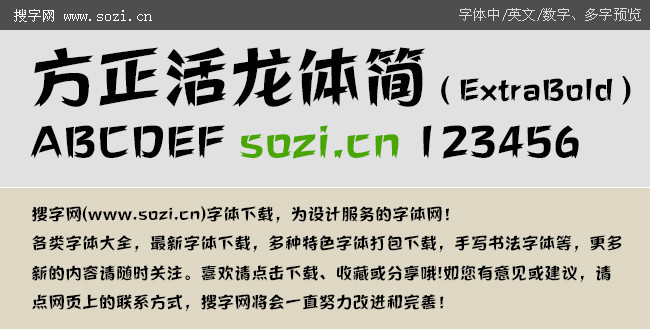
方正活龍?bào)w簡(jiǎn)ExtraBold
搜字網(wǎng)提供一款方正活龍?bào)w簡(jiǎn)中文字體下載,方正活龍?bào)w簡(jiǎn)是方正字庫(kù)全新開(kāi)發(fā)的一款非常實(shí)用的字體,該字體特點(diǎn)是橫、直劃粗細(xì)平均,所有筆劃頭部斜直而末端開(kāi)了叉口,而且點(diǎn),撇,捺,抅等都是弧形,沒(méi)有垂直平行線的,橫劃重心向右上方斜上,讓它活一些,有動(dòng)感和速度,像一條龍?jiān)谔炜诊w舞,可以應(yīng)用于網(wǎng)頁(yè)設(shè)計(jì)、包裝設(shè)計(jì)、海報(bào)設(shè)計(jì)等廣告設(shè)計(jì)場(chǎng)合使用。